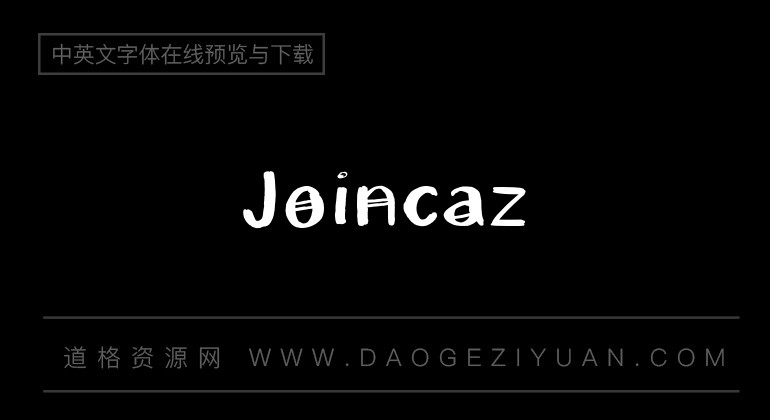
Joincaz
? Joincaz 字体是一款简洁优雅的英文字体,它由著名的设计师Joincaz设计,受到了众多设计师的青睐。它是一款经典的多功能字体,适用于各种设计领域,包括海报、广告、品牌设计、标志设计等,可以满足各种不同的需求。它的特点是简洁优雅、清晰精致、易于辨识,能够为设计师带来更多的创作灵感。
Joincaz是一款非常不错的手写艺术字体,具有很好的视觉感,适合于文化类的宣传设计、商业类品牌的广告和产品包装设计以及个性化文字排版等较多场景。
Joincaz字符映射图